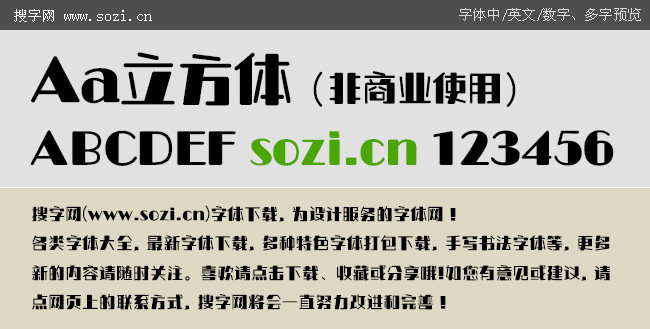
Aa立方體
搜字網(wǎng)給大家提供一款A(yù)a立方體(非商業(yè)使用)中文字體下載,該字體是一款中文藝術(shù)字體,字型方正有趣,筆畫粗細(xì)不一,給人一種立體的視覺(jué)效果,非常有意思,適合書裝設(shè)計(jì)、包裝、海報(bào)設(shè)計(jì)等應(yīng)用(此字體為個(gè)人非商用版,商用可以聯(lián)系QQ:1006760504)。